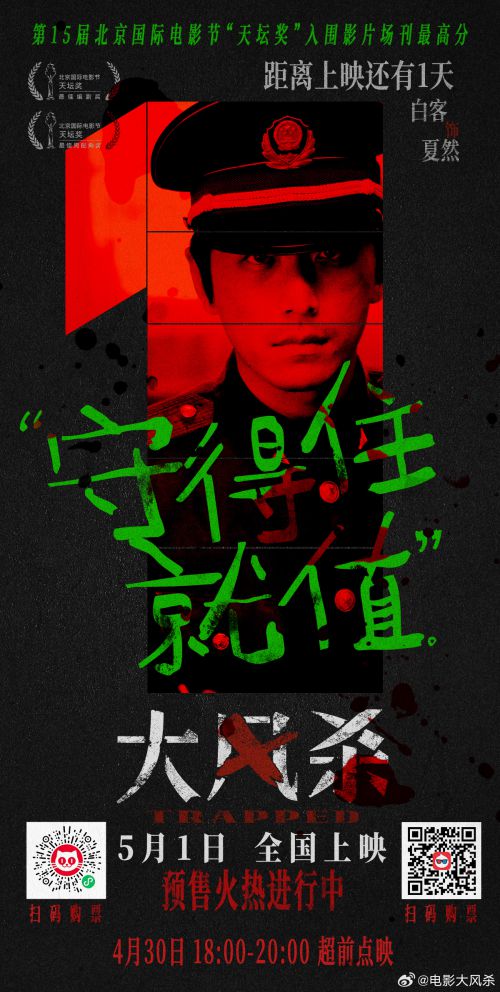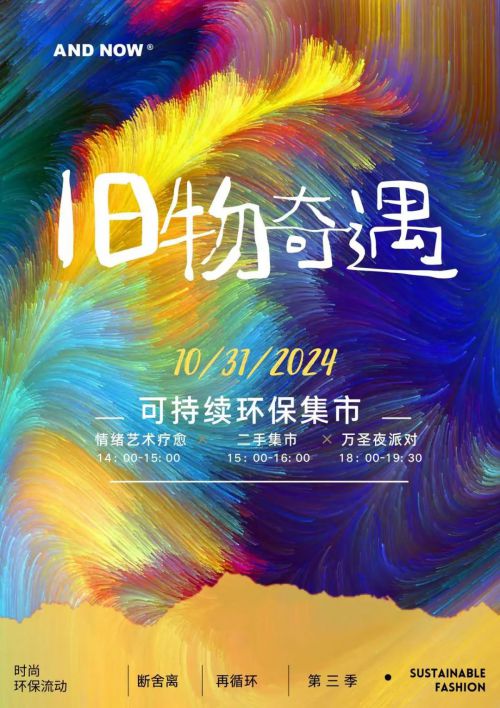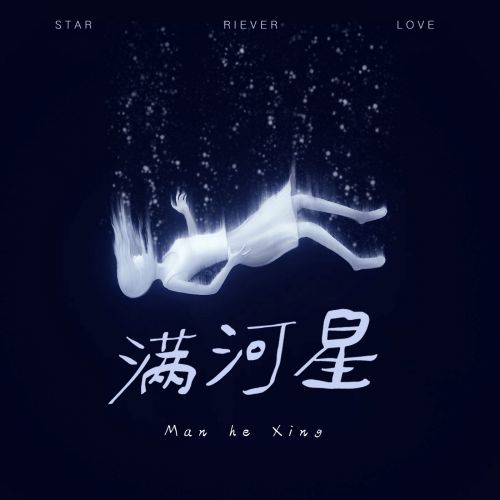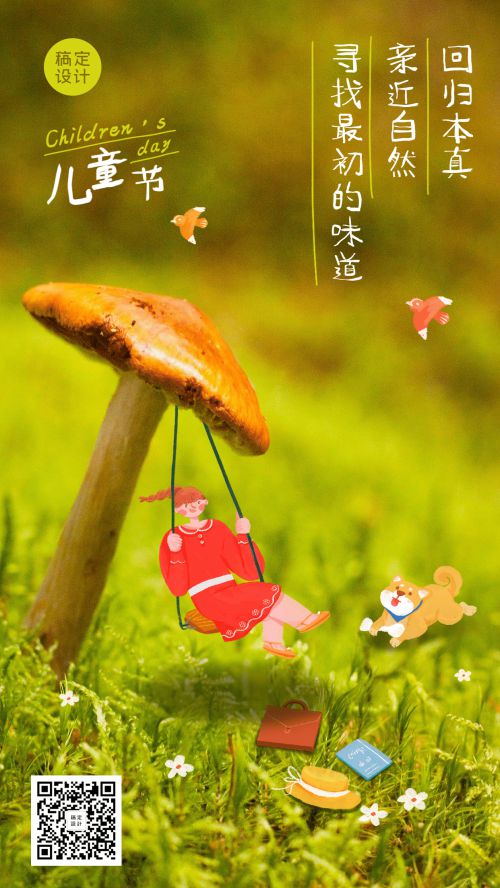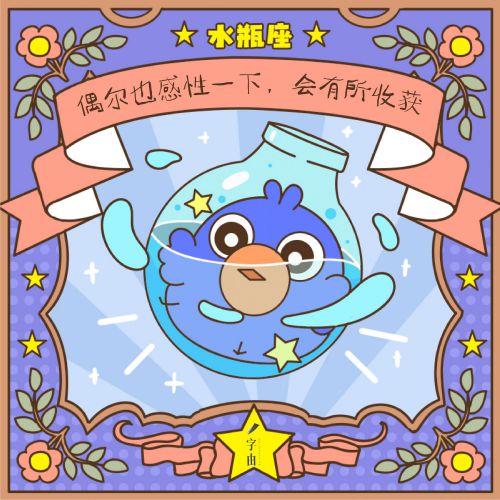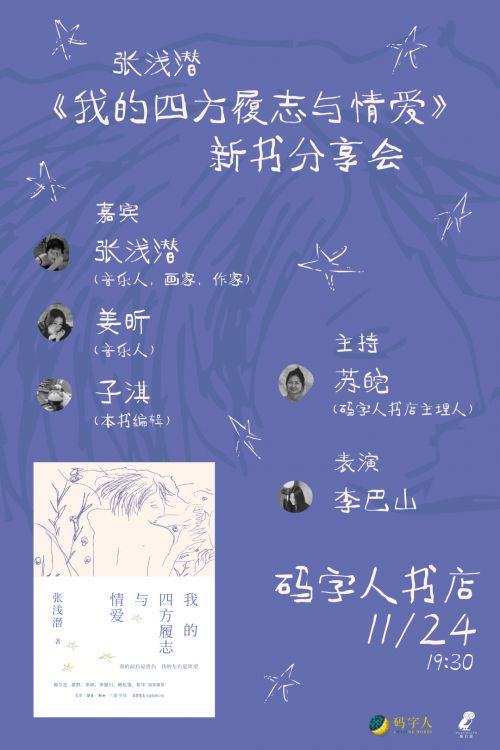
点字稻草人
点字稻草人这款字体是想表现在乡间田野间,稻田丰收,金灿灿的稻谷丰收后,孩童们在田埂间用稻草随意玩耍,堆砌编制草人的情景。 点字稻草人每个笔画就像田间满地的碎稻草、秸秆。自然,淳朴,稻谷的清香,满满的活力,看似随意组合的字型,透露着大地原有的本真跟魅力。 希望大家在运用时感受到稻草的温暖、田间的风。
朱璐
设计师、插画师、动画师,平面设计作品、艺术作品与动画短片多次获得国内外各类奖项。